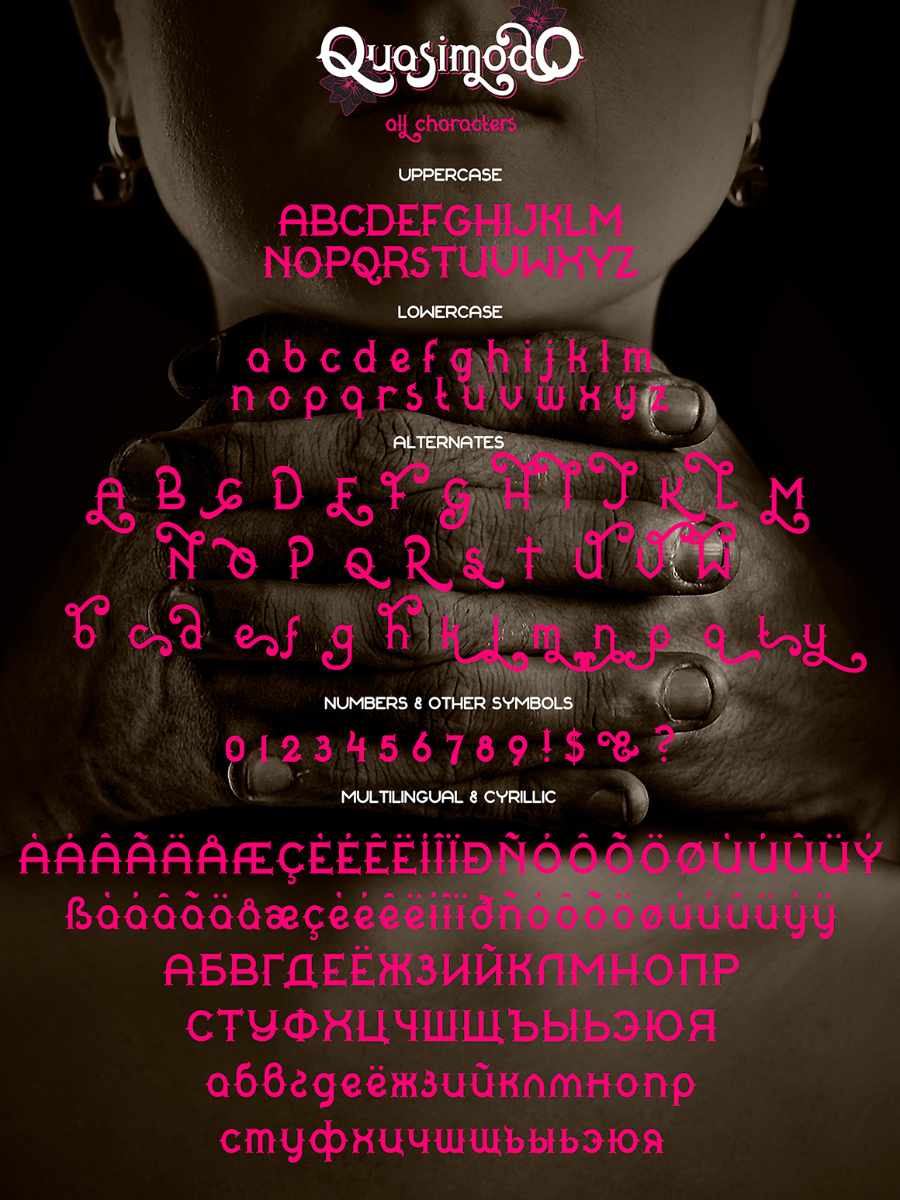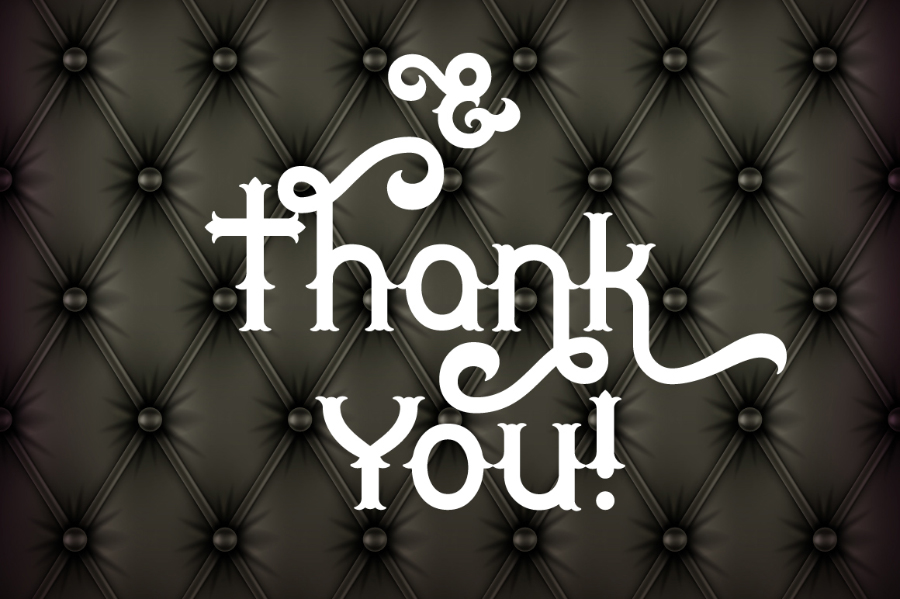
Quasimodo字体免费演示
Quasimodo Typeface Free Demo
Quasimodo字体免费演示是一个有趣的Andriy Dykun曲线字体。这种字体将添加复古或复古的触摸到您的设计。所以如果你正在用老式的东西做一些东西,那这个可以是正确的。此外,它适用于简单的标志设计,网站标题,婚礼设计,网站的菜单字体。 Quasimodo在设计时尚,杂志和美容产品方面也很出色。